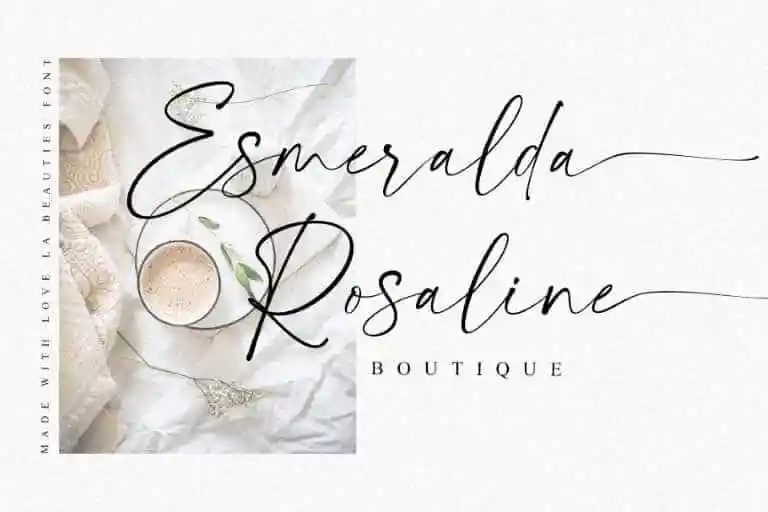
La Beauties Script Font – Download Grátis
A La Beauties Script Font é uma escolha perfeita para designers que buscam dar um toque elegante a seus trabalhos. Com seu estilo refinado e clássico, esta fonte tem atraído projetos de diversos tipos, desde promoções até cartões de casamento. Ela foi criada por vanpatelona na 99designs, um ambiente para designers onde é fácil encontrar novas ideias e inspirações. Com seu charme único e seu caráter quase chic que se destacam ao usar esta fonte em projetos, ela se tornou uma escolha popular para branding e cartões de casamento. Além desses usos mais formais, La Beauties Script é igualmente versátil para aplicação em outros contextos pessoais e comerciais, garantindo sempre um toque elegante e moderno a cada projeto.